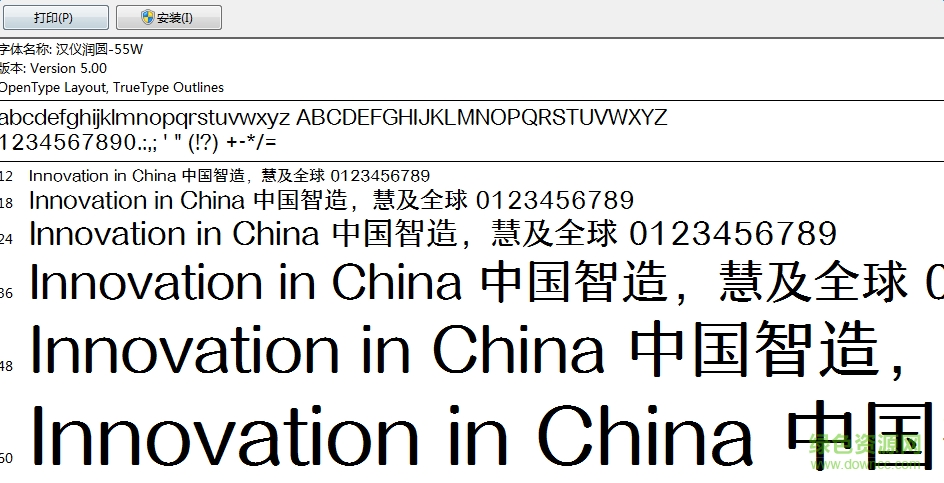
軟件介紹 軟件標簽: 漢儀字體 字體 漢儀圓潤55w book是一款漢儀字體庫中的個性字體,該字體可以廣泛應用于廣告設計、宣傳海報、ppt、影視制作以及任何使用文字的領域,有需要的朋友可以免費下載收藏。字體安裝方法方法一:控制面板/字體/文件/安裝新字體;方法二:直接將字體復制到C:\WINDOWS\Fonts。方法三:針對win7系統(tǒng),用戶只需選中字體右鍵安裝即可。注意事項本站所有字體資源僅供個人學習與參考,如需商業(yè)使用請到相關(guān)官網(wǎng)授權(quán)。 本字體如果商用,請聯(lián)系漢儀字體官方獲得授權(quán)。 軟件截圖 上一張下一張(1 / 1) 安裝詳細截圖 猜你喜歡 漢儀字體 漢儀字體 漢儀字體有哪些?漢儀字體下載大全收錄了所有好看的、經(jīng)典的漢儀字體合集,漢儀字體是由北京漢儀科印信息技術(shù)有限公司創(chuàng)作,這些字體種類齊全,各具特色、應用領域廣泛,喜歡漢儀字體的朋友歡迎來綠色資源網(wǎng)免費下載使用! 查看更多>> 阿里巴巴普惠字體 26.00M/中文/0.8/官方ttf版下載 漢儀天宇風行體 21.41M/中文/5.0/下載 漢儀蘇澤立行楷精修版簡 3.01M/中文/4.0/免費版下載 漢儀正圓(共7款) 17.96M/中文/2.8/ttf免費版下載 漢儀可愛字體打包 41.20M/中文/5.0/14款下載 漢儀曉波花月圓字體 1.89M/中文/0.0/下載 其他版本下載 標題 大小 更新日期 下載 漢儀潤圓 35w字體 2.51M 2017-02-15 下載 漢儀潤圓 45w字體 2.86M 2017-02-15 下載 漢儀潤圓 65w字體 2.91M 2017-02-15 下載 漢儀潤圓 75w字體 2.83M 2017-02-15 下載 漢儀潤圓系列字體 14.00M 2017-05-15 下載 下載地址 電腦版 漢儀潤圓 55w字體 點擊報錯 軟件無法下載或下載后無法使用,請點擊報錯,謝謝! 關(guān)閉報錯反饋 請描述您所遇到的錯誤,我們將盡快予以修正,謝謝! *必填項,請輸入內(nèi)容 本類最新 漢儀孟瑞體ttf v1.0 官方版 漢儀字庫免費 132款 阿里巴巴普惠字體 官方ttf版 漢儀字體打包大全 for Mac 蘋果電腦版_ 共131款字體 漢儀純愛情書拼音體 ttf版 漢儀北魏寫經(jīng)w字體 免費版 相關(guān)文章 Photoshop字體安裝使用方法和技巧 如何解決“無法新增字體”問題 Win 7系統(tǒng)安裝字體方法 網(wǎng)頁字體大小設置方法 怎么改網(wǎng)頁字體大小 在Linux系統(tǒng)中安裝字體的幾種方法 windows7字體顯示問題:打開某些程序的時候顯示的是亂碼 用戶評論 熱門評論 最新評論 發(fā)表評論 查看所有評論(0) 昵稱: 請不要評論無意義或臟話,我們所有評論會有人工審核. 字數(shù): 0/500 (您的評論需要經(jīng)過審核才能顯示)